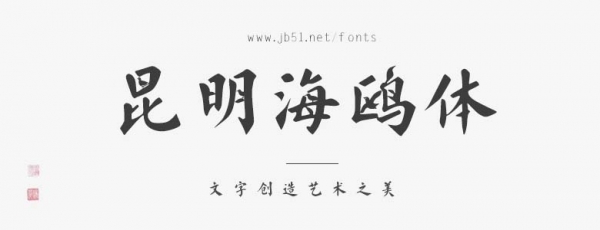
昆明海鷗體創(chuàng)作者、字體家AI神筆造字負(fù)責(zé)人、中國當(dāng)代著名書法家葉根友為昆明送上專屬的新年文化禮物——全國首款城市定制型海鷗主題字體,這款被命名為“昆明海鷗體”的字體,全套共6763個字,即日起就可供全國設(shè)計工作者免費使用。
“昆明海鷗體”的“昆明”兩字中的都有紅嘴鷗的形象,特別是“昆”字中的紅嘴鷗形象,設(shè)計團隊先后做了10多種造型,最后才選定一只站立紅嘴鷗的形象。除了昆明兩字中有海鷗形象之外,“滇池”“春城”“翠湖”“平安”“美滿”等漢字的筆畫中都有紅嘴鷗的各種姿態(tài)。